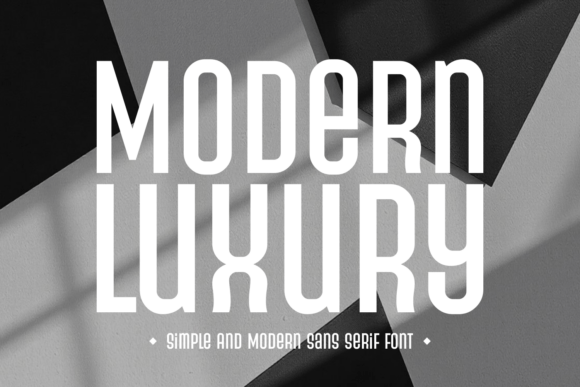
Modern Luxury
Modern Luxury – La police qui redéfinit l’élégance moderne
Vous cherchez une typographie sans‑serif capable d’ajouter une touche de raffinement à vos créations ? Modern Luxury répond à cet appel avec brio. Conçue spécialement pour les projets premium, elle s’inscrit déjà comme une référence incontournable dans le monde du design contemporain.
- Design polyvalent : parfaite pour les bannières, les logos, les supports imprimés, les créations Cricut, les stickers et même les magazines d’été.
- Style distinctif : allie modernité et élégance, offrant un rendu à la fois bold et sophistiqué qui capte immédiatement l’attention.
- Adaptée aux tendances : idéale pour les campagnes sur les réseaux sociaux, les visuels de la Fête des Mères ou tout projet fashion qui suit les courants actuels.
- Support multilingue : intègre naturellement les caractères d’Europe de l’Est, garantissant une cohérence typographique quel que soit le marché cible.
- Logotype prêt à l’emploi : grâce à sa structure unique, Modern Luxury se transforme facilement en identité visuelle forte pour les marques qui souhaitent se démarquer.
En plus de son esthétique luxueuse, Modern Luxury se distingue par sa lisibilité exceptionnelle même à petite taille, ce qui la rend idéale pour les supports numériques comme les stories Instagram ou les publicités Facebook.
Pourquoi choisir Modern Luxury ?
- Un rendu high‑end qui renforce la perception de valeur de votre marque.
- Une flexibilité d’utilisation qui couvre du print au digital sans perte de qualité.
- Un design qui crée immédiatement une vibe de luxe et de modernité, parfait pour les projets premium.
- Une compatibilité avec les outils de découpe (Cricut, Silhouette) pour des créations artisanales haut de gamme.
En résumé, Modern Luxury n’est pas seulement une police : c’est une expérience de marque. Que vous travailliez sur un logo, une couverture de magazine ou un visuel pour les réseaux sociaux, elle apporte ce « cool love‑infused touch » recherché par les designers les plus exigeants.